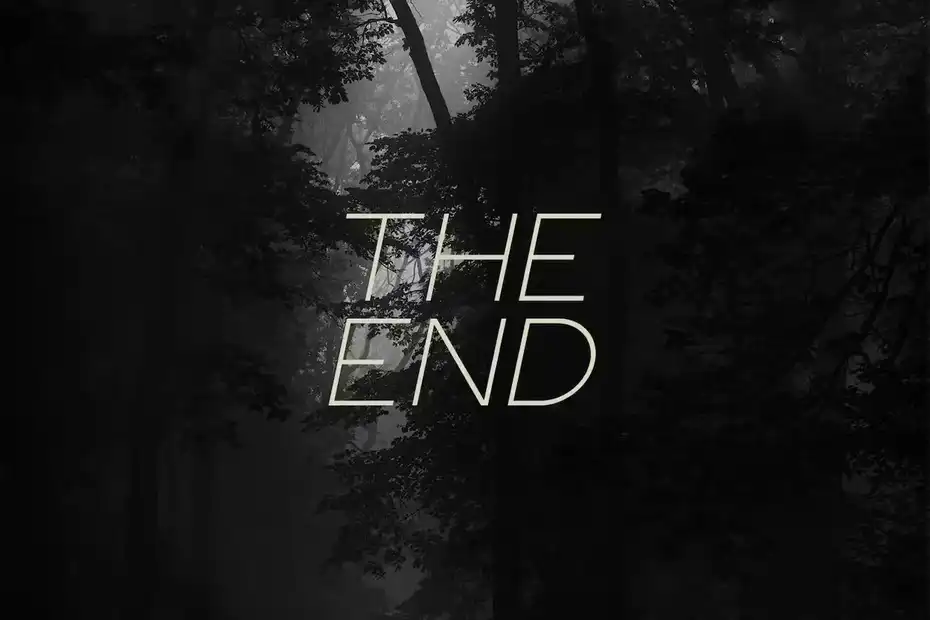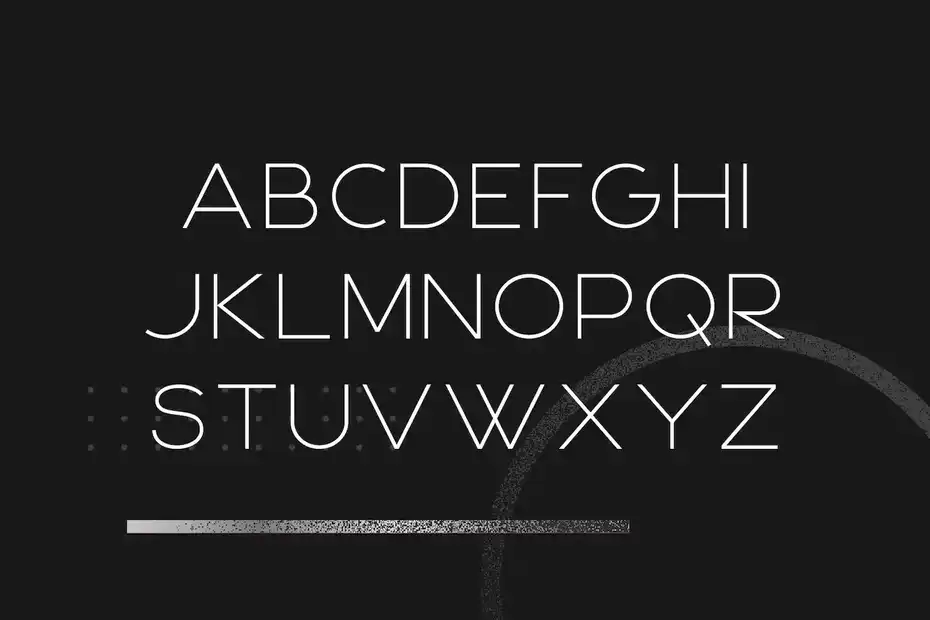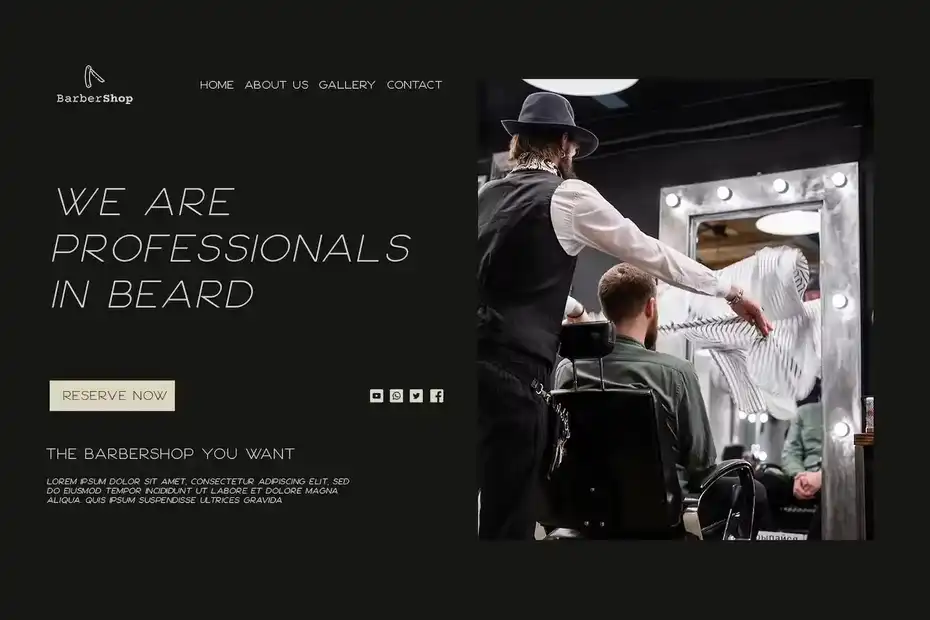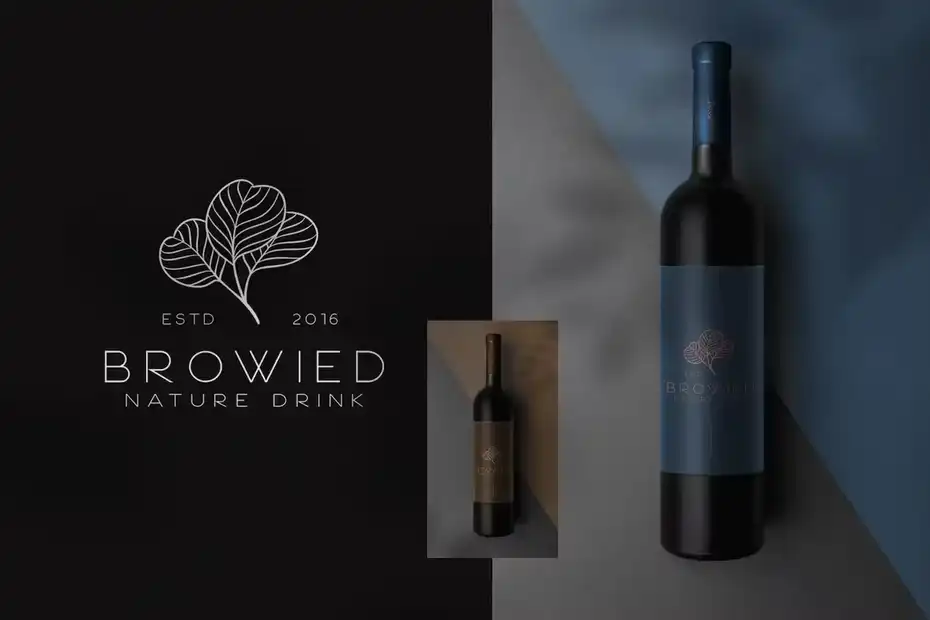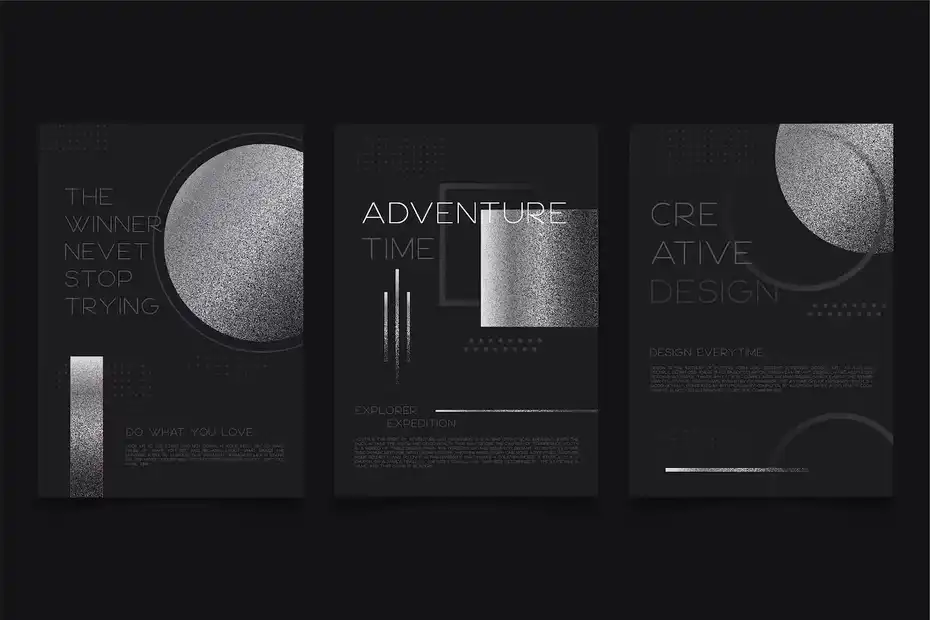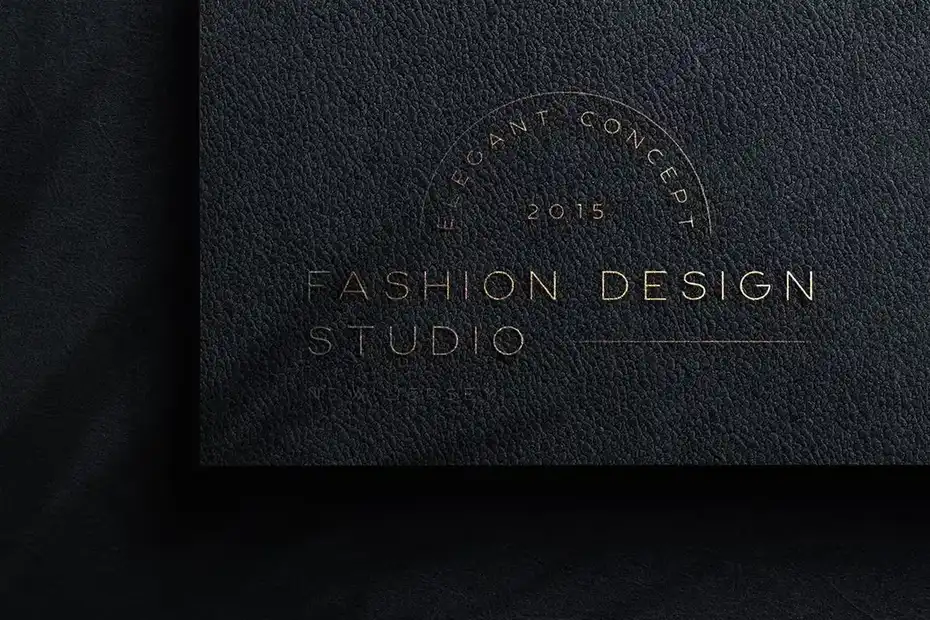
دانلود فونت سنس سریف مدرن Brown Austin – Modern Sans Serif Font
دانلود فونت سنس سریف مدرن Brown Austin – Modern Sans Serif Font : این مجموعه شامل یک فونت انگلیسی مدرن به سبک Sans-Serif است که برای لوگو، کارت دعوت، سربرگ و غیره مناسب میباشد. فونت های مدرن در کارهای گرافیکی بسیار جذاب و کاربردی هستند، می توانید برای مشاهده فونت های حرفه ای بیشتر دسته بندی فونت انگلیسی مدرن را در سایت سیجی کوک بررسی کنید.